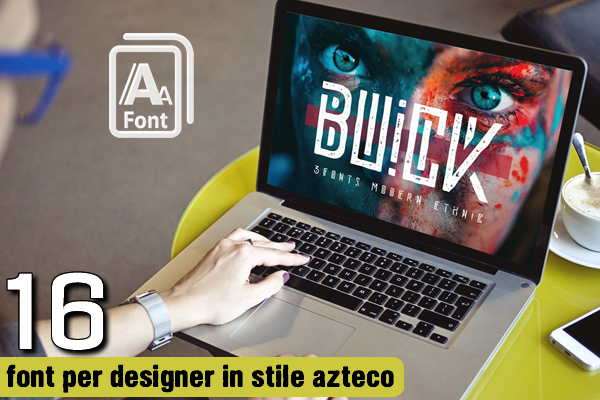
Se cercate un modo per dare ai vostri design un tocco esotico e antico, potete dare un'occhiata sul sito Just Creative e alla loro raccolta di 16 font in stile azteco.
Questi caratteri tipografici si ispirano all'arte intricata e affascinante della civiltà azteca, nota per i suoi elaborati geroglifici, le splendide piramidi e le ricche tradizioni culturali.
I font aztechi possono aggiungere profondità e carattere a qualsiasi progetto, sia che si stia creando un sito web, progettando la copertina di un libro o creando un logo.
Evocano lo spirito di un'affascinante epoca storica e offrono un modo unico per il testo di catturare l'attenzione e trasmettere informazioni con un senso di mistero e intrigo.
Gli stili dei caratteri aztechi sono visivamente sorprendenti e immediatamente riconoscibili con angoli acuti, forme geometriche e linee audaci.
Sono un modo potente ed evocativo per aggiungere profondità e carattere a qualsiasi progetto.
16 font per designer in stile azteco